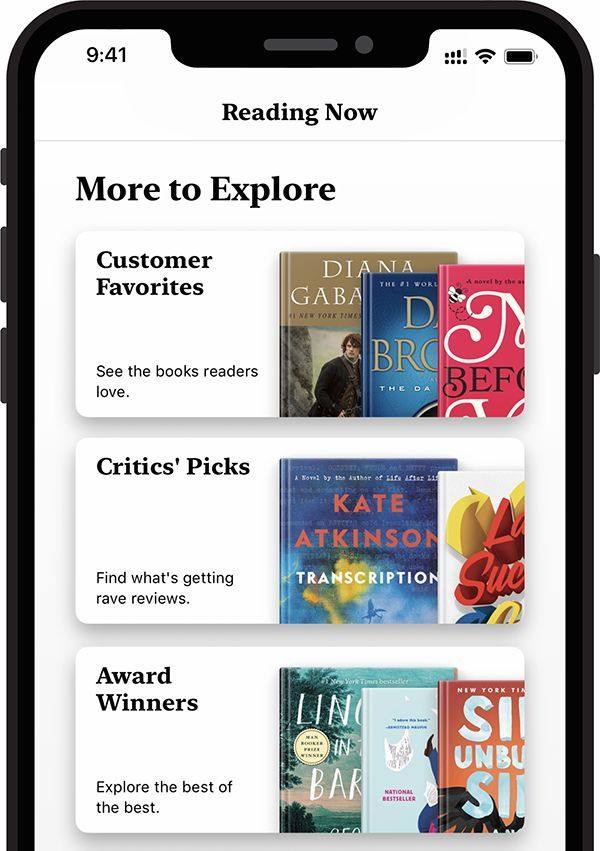
全新设计的 Apple Books 中布满了衬线(Serif)字体
九月,苹果(Apple)公司在其最新的 iOS 系统中,为 Apple Books (苹果公司电子阅读器软件)带来了全新的设计。在这次设计更迭中,所有的标题字体都被换为了衬线体(Serif),要知道,这几乎从未在 iOS 系统中发生过。在屏幕上使用西文衬线体的机遇,似乎近在眼前。
时间回到二〇一〇年,iPhone 4 横空出世。抛去其精妙绝伦的工业设计不谈,iPhone 4 是第一款真正意义上带有接近纸质视觉效果屏幕的民用电子设备。就像电力、互联网、微型计算机的发明一样,从这件事物出现以后,之前的时间和之后的时间就被立刻划分成了两个时代。从这一刻起,在屏幕上欣赏像素点这种事,只能被当作一种情怀了。
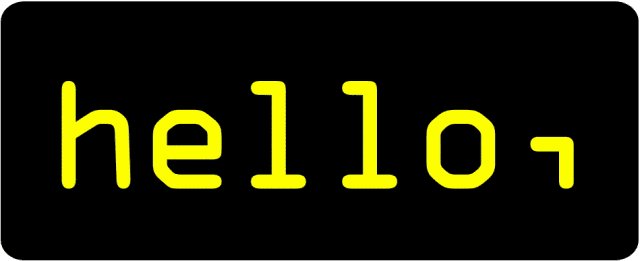
苹果公司将 iPhone 4 所携带的高清屏幕称之为视网膜(Retina)屏幕。伴随着视网膜屏幕的出现,此前还看得过去的手机屏幕变得再也无法忍受。自此以后,一切都变得更为清晰。像素点、颗粒化的图标与点阵字,再难寻踪迹。与此同时,设计(Design)也同样经历着一场革命。屏幕的进化升级解开了一个桎梏已久的视觉枷锁,从而拉近了屏幕与纸面的距离。
字体的设计也逐步突破了屏幕“分辨率”的限制。在这之前,要想在屏幕上展示“衬线体”,那可真是要难为人。但彼时也终于有机会得以在屏幕上施展拳脚。
为防止你迷失在即将到来的术语迷潭,迅速带上这个快速启动包。所谓衬线,就是我们常见的,在字母或笔划边角处起到装饰作用的那些细线,这些饰角来自于古罗马时代工匠们在石碑上的悉心凿刻。伴随着现代平面设计发展的近百年的历史,优秀的设计师们不断创造了大量优秀的衬线字体。然而,从家用微型计算机出现之后,它们就统统都被挡在麦金塔那块 512 x 342 px 分辨率的单色屏幕之外了。
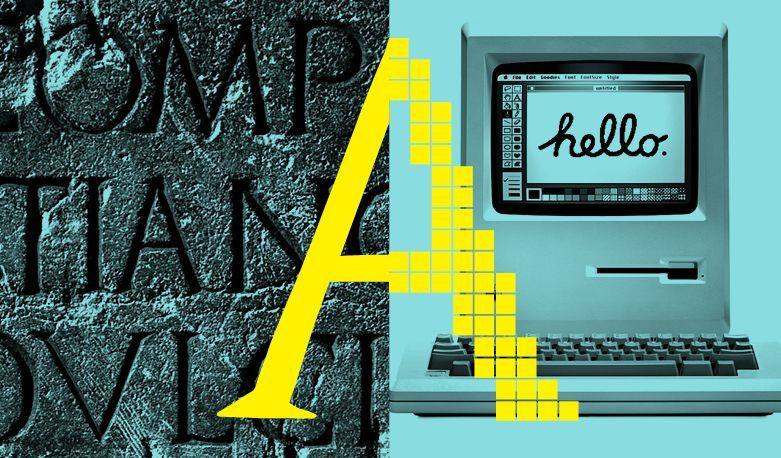
石碑与屏幕上的字体(第一代 Mac 上的 hello,注意,上面并没有“衬线”)
因为屏幕技术的限制,想要在屏幕上展现出好看的衬线字角非常困难。而字体在屏幕上的显示也经历了从适配屏幕到顺应屏幕的历程。
在光谱的另一头,对于屏显衬线体的需求一直没有停止。
媒体,天然对字体选择有需求。好的媒体会试图为自己的内容塑造鲜明的特征。选题、文风、视觉缺一不可,而要拥有这种特征,在视觉呈现方面,字体的选择尤为重要。
许多优秀西文媒体的设计师们为了达成这一目标殚精竭虑。刊头、一级标题字体,和正文字体都经过了最优秀设计师的精心打磨与挑选。《纽约客》(The New Yorker)的刊头字体 Irvin 识别度之高,无论任何时候只要扫一眼版面哪怕在数米开外也能立即认出这是《纽约客》。《连线》(Wired)、《卫报》(The Guardian)与《纽约时报》(The New York Times)更甚,所有的文字字体都经过了严格地设计与选择,以求读者能更准确地识别到自己。
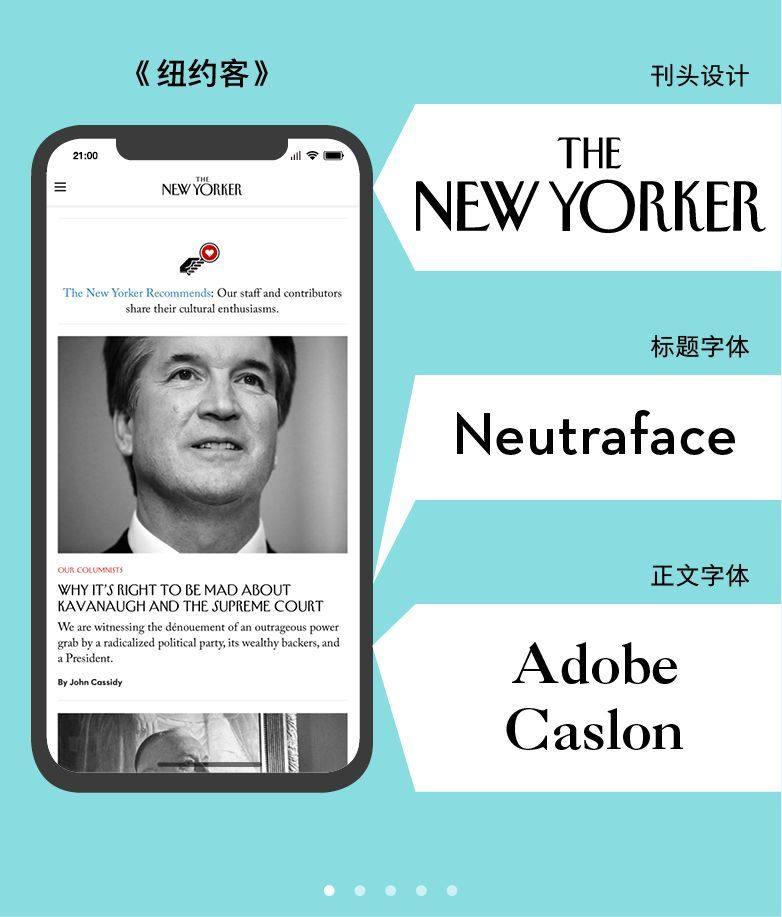
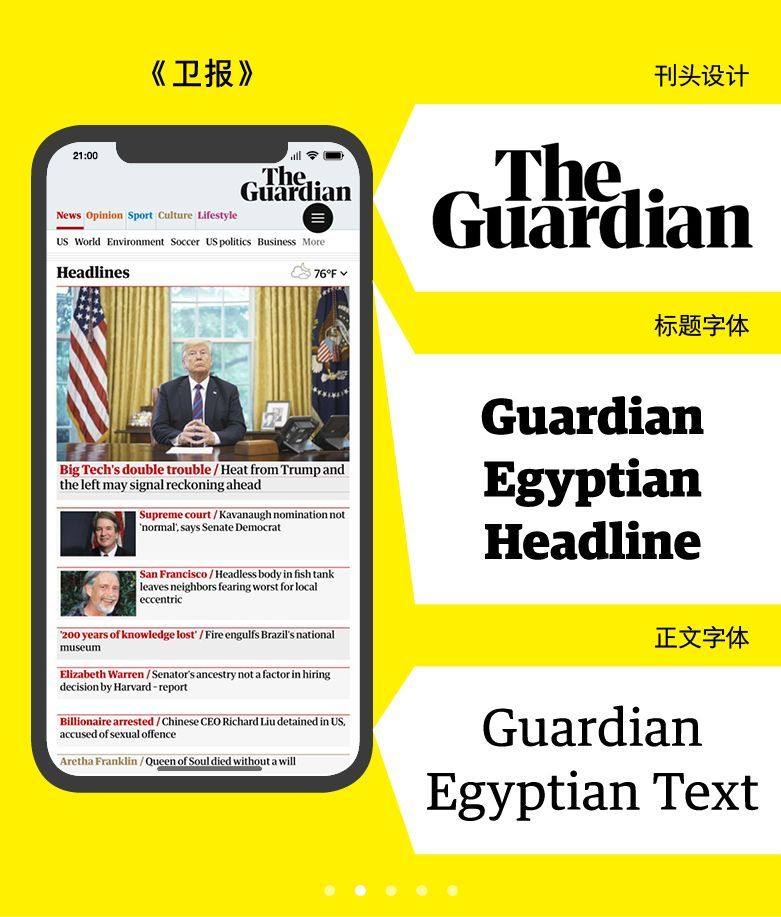
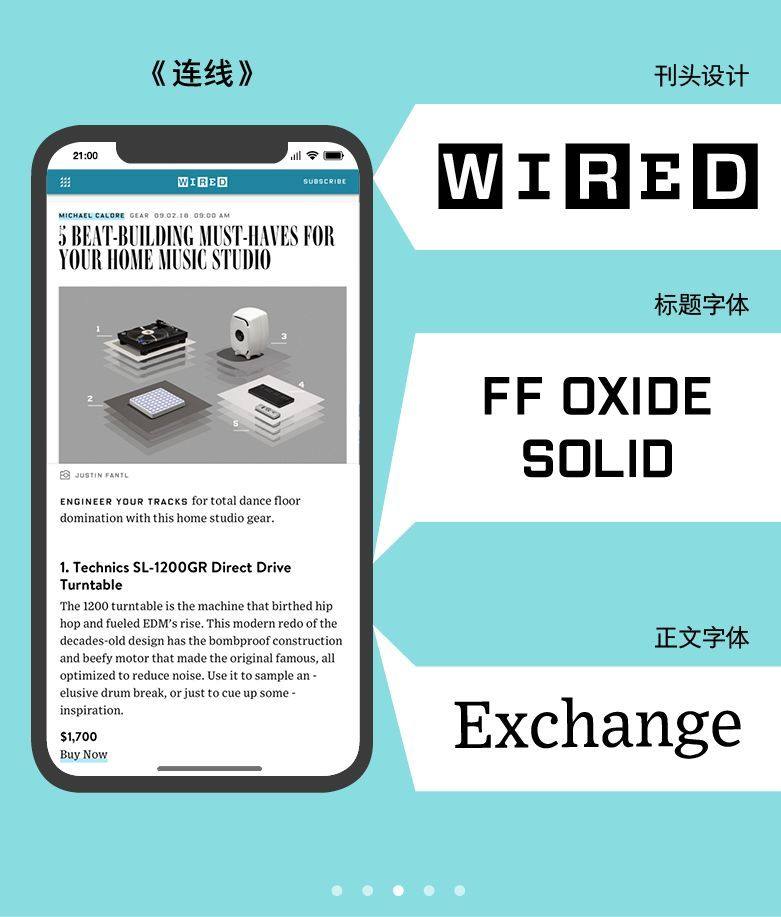
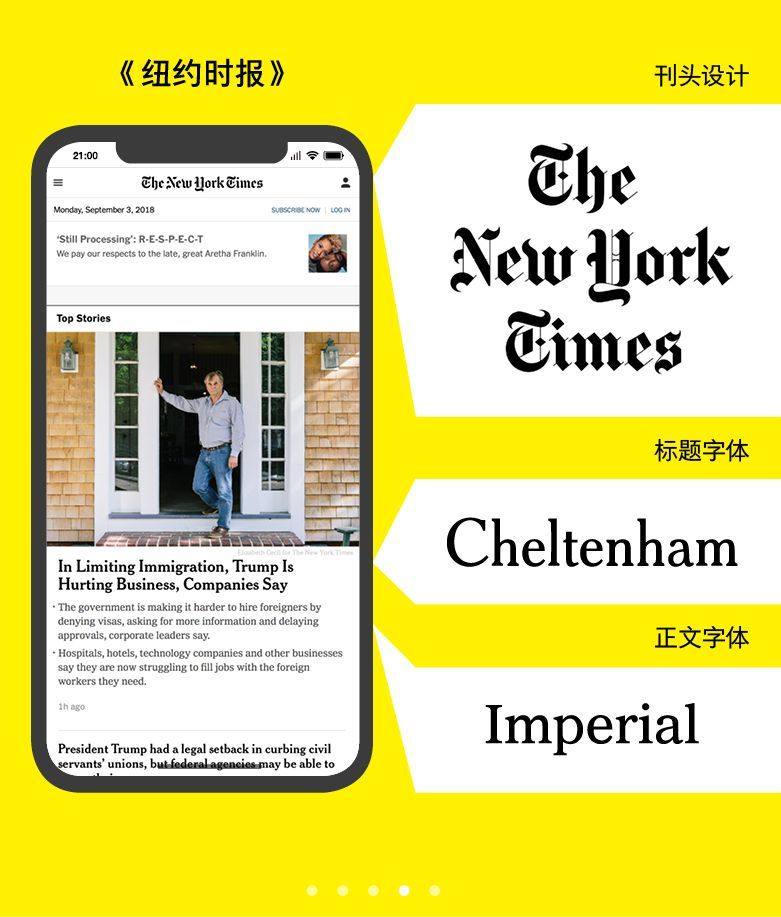
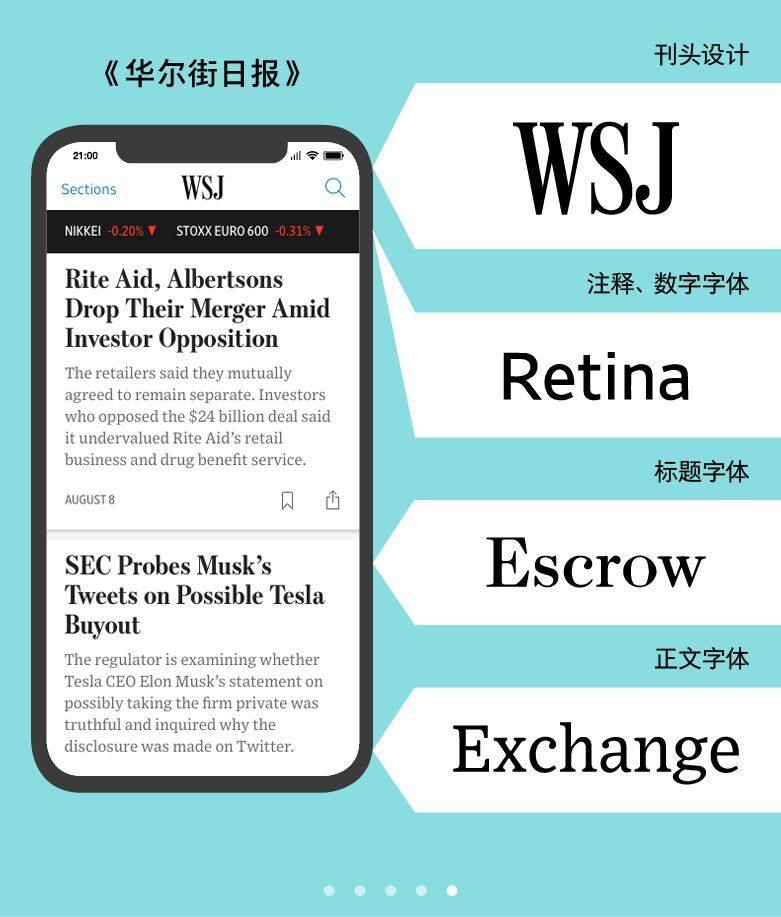
西文新闻媒体的屏显字体搭配
无独有偶,这些被选择的字体居然大多都拥有优雅的曲线与衬线。但很明显,上不了屏幕,上了也看不清。要在屏幕上显示这些经过精心设计的衬线字体,成了一件令人头疼的事情。这些媒体网站很可怜地只能被迫在默认的系统字体中做选择,统一视觉风格这种事,只能暂时先按捺下来。
《华尔街日报》网页版字体的变化历程
正是因为 iPhone 4 与高清屏幕(比如前文提到的视网膜屏幕)的普及,令这些媒体在屏幕实现字体统一有了可能。
二〇一七年,《华尔街日报》的设计师马修 · 斯特伦(Matthew Ström) 为《华尔街日报》重新设计了整体版面。这次改版的目标之一,就是在《华尔街日报》的屏幕产品和纸质产品一统视觉风格。马修选用了三款字体(Escrow,Exchange,与 Retina),既在纸面上风格鲜明,也在屏幕上清晰可见。
《华尔街日报》用三款字体统一了纸面与屏幕的设计
Escrow 平衡的字形结构和笔划间的高对比度为整个《华尔街日报》设定了一个独特的品牌形象,既有益于读者识别,又提高了阅读的舒适度,特别在像手机这样的小屏幕上。
Exchange汲取了来自历史的经验。一八五〇年代的英国爱奥尼式衬线字体(Ionic)的衬线竭尽所能得夸张,各自拓宽每个字母的字面,字母与字母之间的衬线紧紧地连接在一起。Bell Gothic 这种出生就带着浓浓新闻报纸气的字体,小写字母的内外设计截然不同,内部故意夸张的字怀造成不对称的状态令它的外部看起来坚固笔直。Exchange 融合了这两种经验,让其变得清晰可读,又严肃可靠。
二〇〇二年,To-bias Frere-Jones 计划设计 Retina,他想要一款用最小号字打印出来依旧无比清晰的字体,很幸运,在屏幕时代,Retina 也延续了这一特性。
于是,在这三款字体的帮助之下,马修重塑了《华尔街日报》在电子屏幕上的阅读体验,统一了其在纸面与屏幕上的品牌形象。
想要达成这一点,高清屏幕功不可没,低分辨率的屏幕无法准确地传达西文媒体在字体上的巧思。现在,这些限制已经不复存在。
西文新闻媒体应用的首页界面设计
与中文网络的情况类似,经历了漫长的低清屏幕时代,英文媒体的读者们已经开始厌倦在屏幕上看到泛滥的无衬线体了。在同质化的屏幕界面上,使用衬线体为读者提供了另一种阅读选择。合适的衬线字体被引入到屏幕中,为单调的无衬线字体世界带来了新鲜的阅读体验。(根据设计博客 Webdesignerdepot 的数据显示,选择衬线字体已经成为拉丁语系一种新的潮流。)